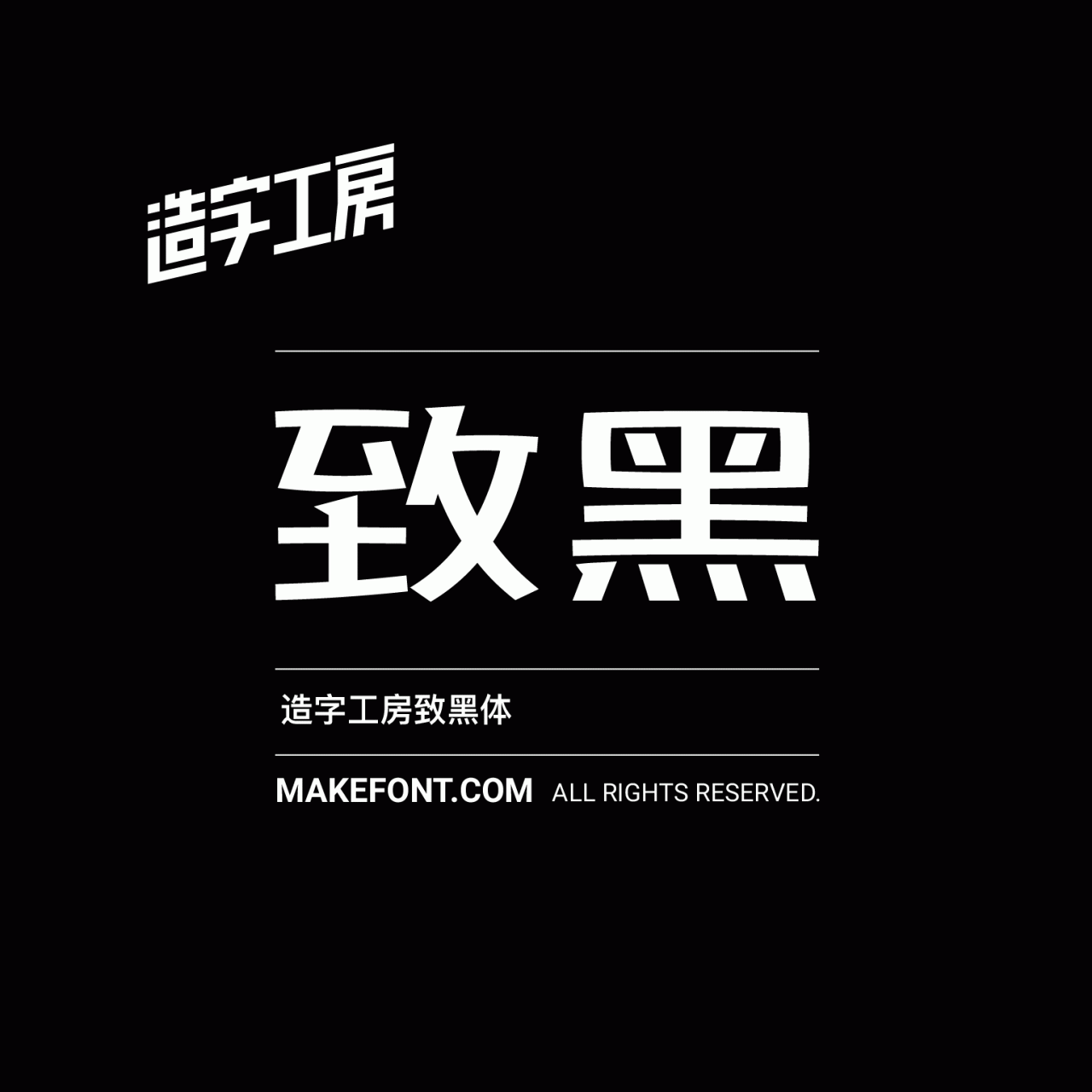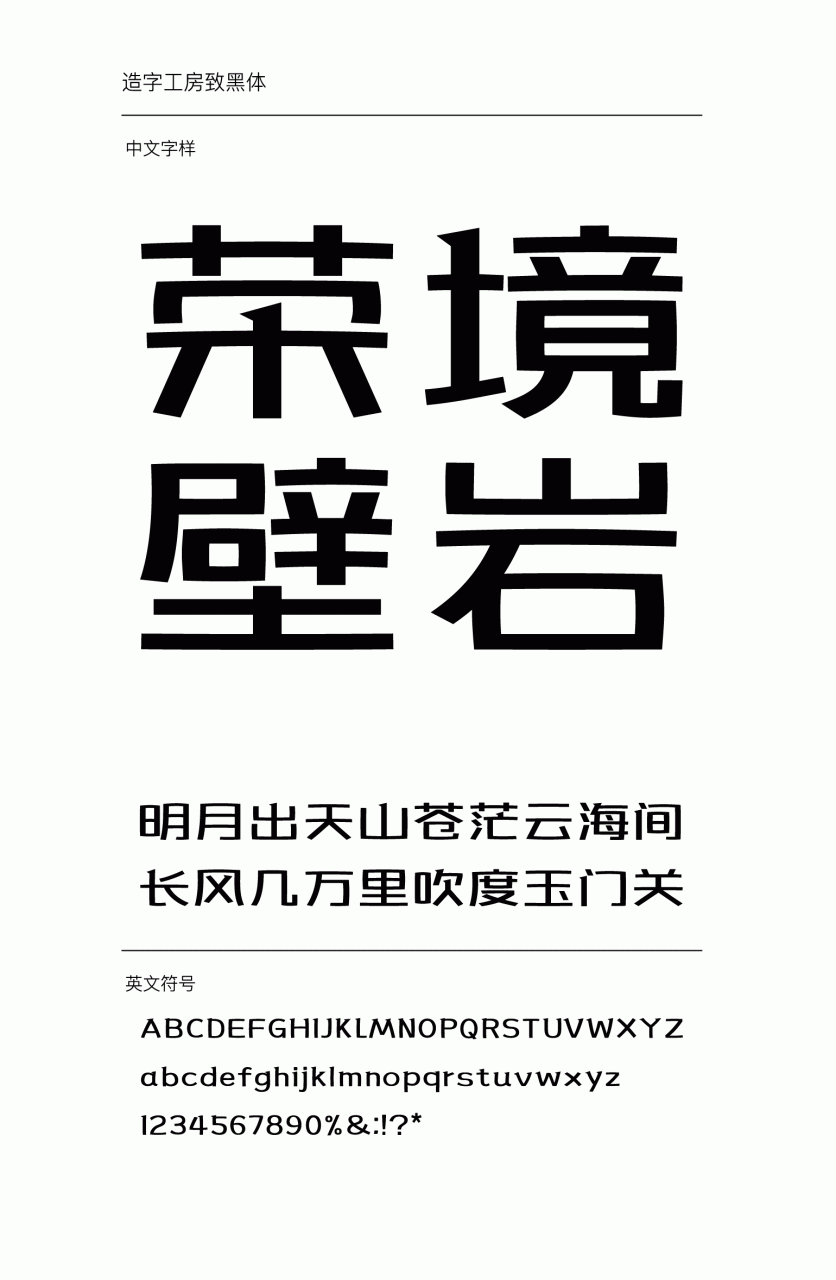
造字工房致黑常规体设计说明
造字工房致黑体,字形结构严谨而疏朗、形疏而气紧,横平竖直的笔画中加入弧度的处理,刚正而不失盈润,局部笔画加入了尖突的效果,让字形更显英朗气质。此款字体适用于报刊杂志及书籍、画报的主副标题和个性品牌设计推广等环境。 本字体为简体字库,采用OpenType/CID格式,Adobe-GB1-5编码。基于中华人民共和国GB2312-80字符集标准,另按需添加101个汉字。共收容字数6864CJK汉字,ASCII常用字符100个。